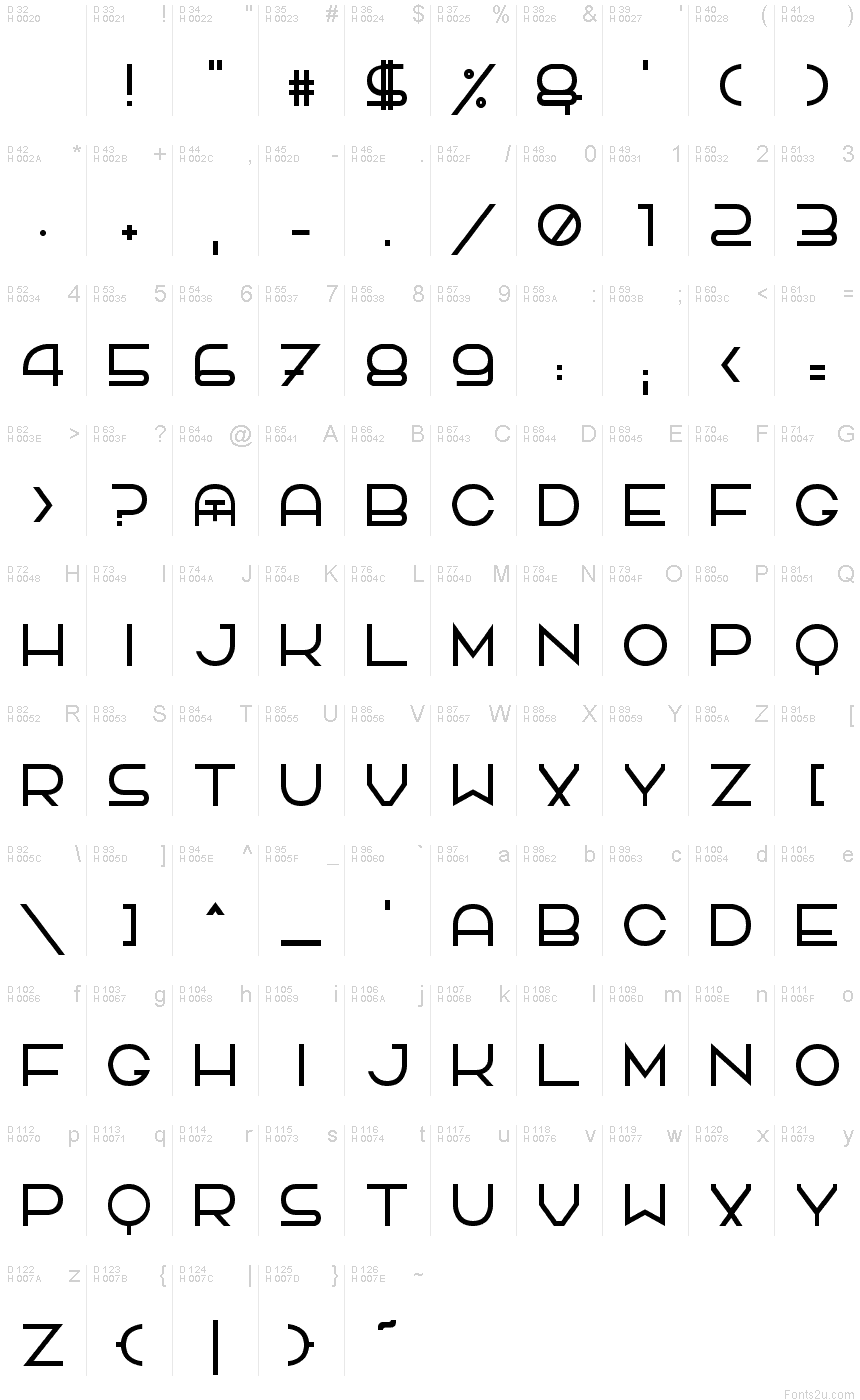
TPF Quackery
خط TPF Quackery من تصميم Christoph Scheiblhofer هو خط عرض (Display) مجاني بأسلوب ريترو مع لمسة واضحة من فن الآرت ديكو (Art Deco). تمزج الحروف بين الأشكال الدائرية العريضة والضربات المستقيمة والمتساوية، مما يمنح الخط طابعاً أنيقاً ومعمارياً بعيداً عن الطابع الحنيني التقليدي أو المبالغ في مرحه.
يناسب هذا الخط عناوين الملصقات، وأغلفة الأسطوانات، وقوائم المشروبات، وبطاقات العناوين، وأي عمل تجاري يتطلب سطراً قصيراً من النص ذي طابع عصري انسيابي. كونه خطاً مجانياً، فهو خيار مقنع بشكل خاص للشعارات (Monograms) وأغلفة التصاميم، حيث تضفي أشكاله الدائرية الواسعة وهندسته المختزلة على الأحرف الكبيرة حضوراً حاداً يشبه الشعار (Emblem).